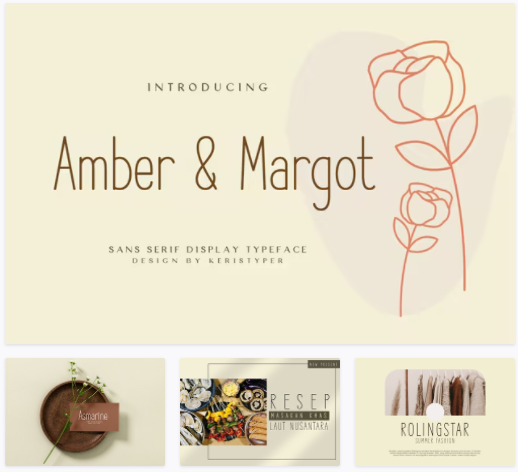
Представляем вам шрифт Amber & Margot the Sanserif Fun Font Это современный, шикарный и элегантный рукописный шрифт, который придаст привлекательный дизайн вашему сайту, шаблону, блогу, подписи к фотографиям, ремеслу, продвижению бизнеса, постам в социальных сетях, цитатам и многому другому ! Включая возможность альтернативных заглавных букв, чтобы сделать ваш дизайн более красивым !